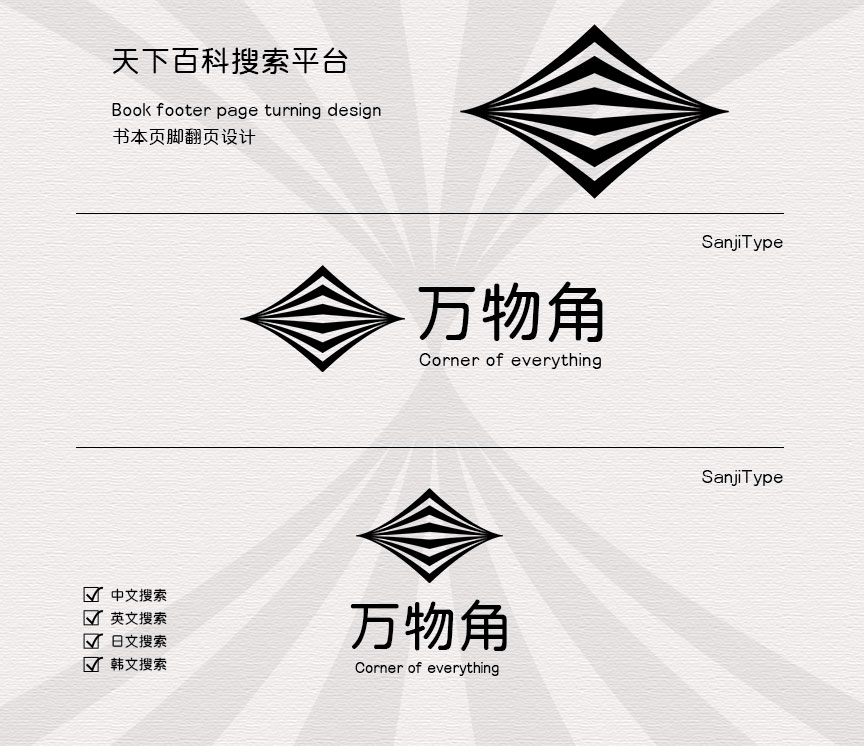
三极圆体简家族
字体名称:三极圆体简-粗
设计师:曾南
所属分类:圆体
三极圆体简是一款家族字体,字形稳重,结构严谨,字面较大。起笔收笔处为圆形,折笔圆弧,撇捺外延、增强了字体的识别性,字形更加圆润大气。适用于各类便携式屏幕的系统嵌入字体,以及传统印刷媒介的标题与正文排版。在品牌形象设计中作为logo设计性文字视觉效果更佳。
适用媒介:报纸、杂志、书籍、广告、标志、宣传册、空间导视、包装、影视、屏幕显示、交互设计。